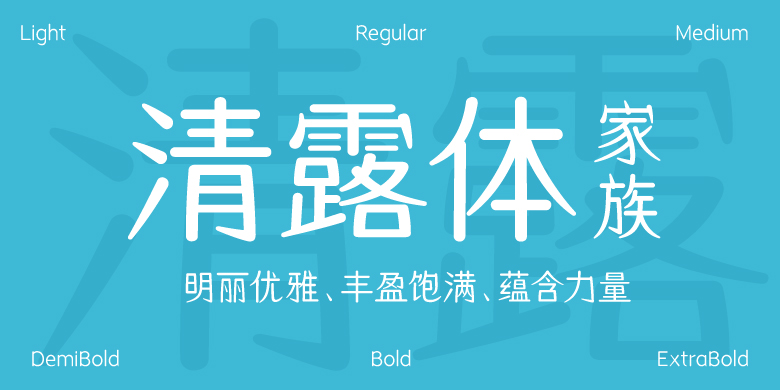
方正清露体家族
方正清露体家族,这款字体结构工整、笔画清晰,兼顾美观与易读性,适用于标题、正文、海报、包装、LOGO 等多种场景。字形优雅稳定,风格百搭耐看,适配日常排版与创意设计,让文字呈现更舒适、更具质感。方正清露体家族一笔一画,皆是细节,以均衡的比例、流畅的线条打造舒适视觉体验,字形端正大气,风格简约现代。无论是商业设计、品牌宣传还是日常排版,都能轻松驾驭,让文字更有格调与力量。方正清露体家族字体下载。
方正清露体的创作灵感来源于自然。这套字体的笔形设计源自于“凝结在草叶上的露珠”这一自然景象。通过笔形从尖细到圆钝的变化模仿露珠从草叶上滑过的轨迹,通过增加笔画的韧度和弹性彰显出对植物生命力的崇尚。作者希望这套家族字体可以在字重变化中呈现出丰富而感性的姿态,既明丽优雅、温润动人又丰盈饱满、蕴含力量。